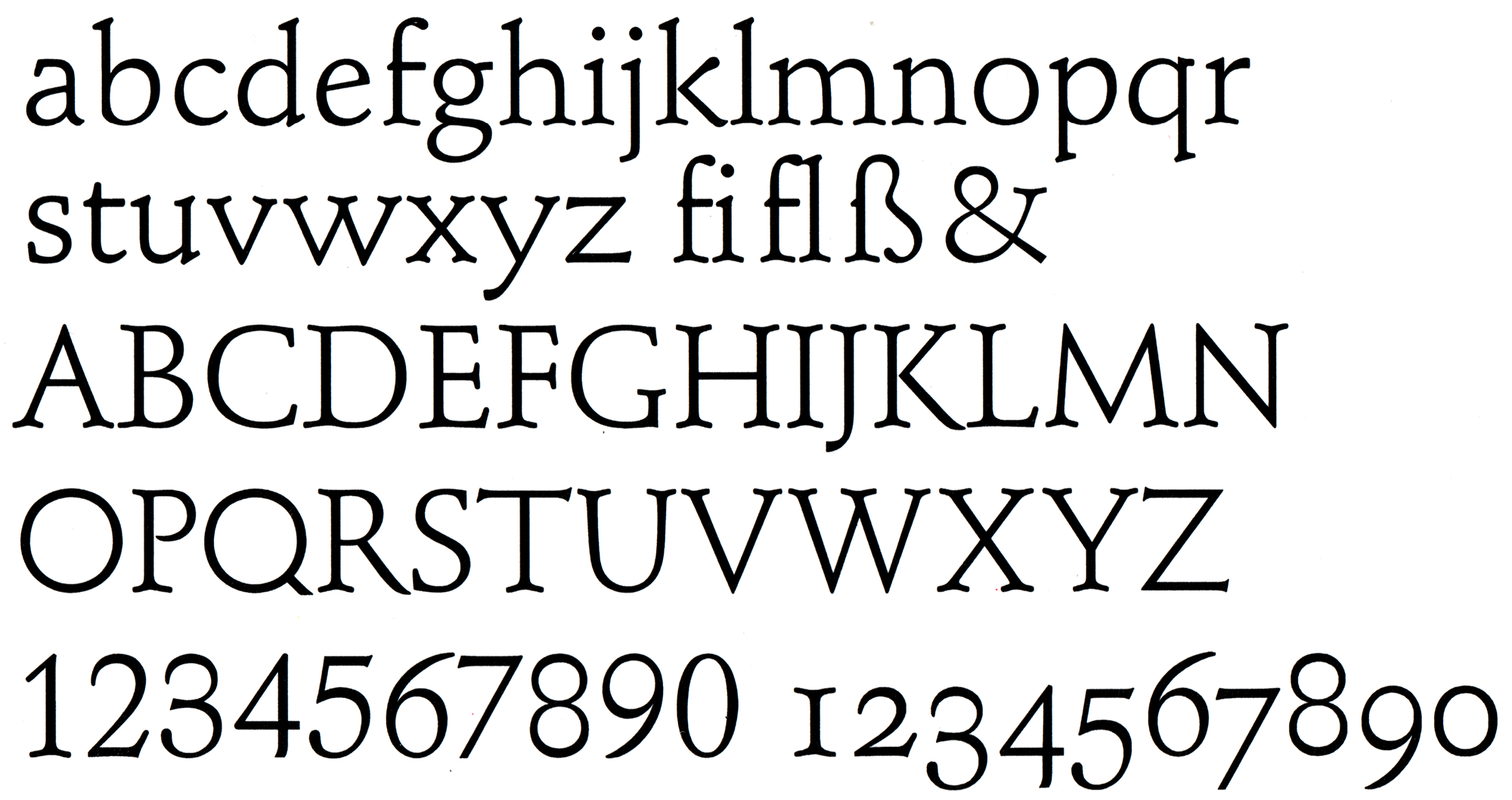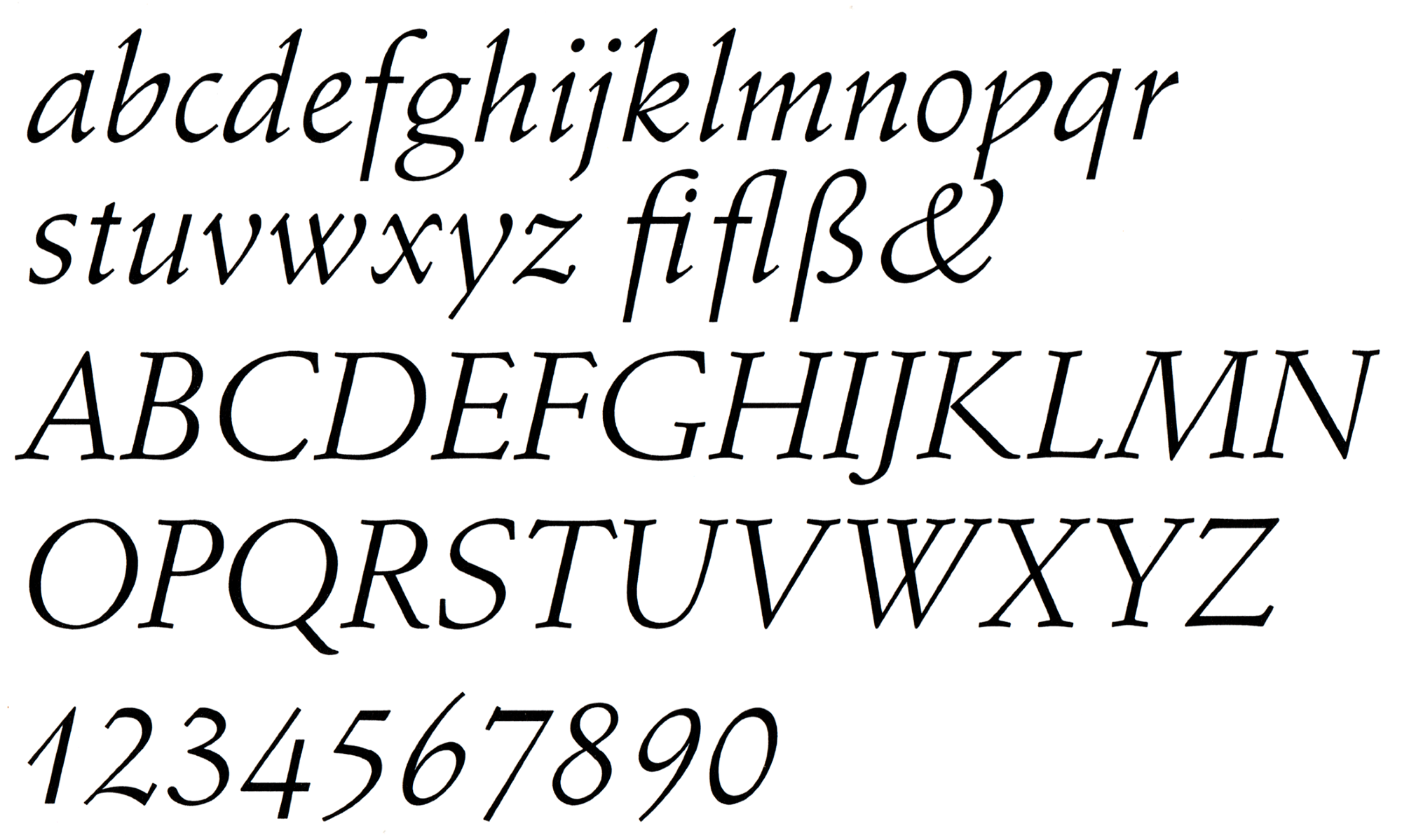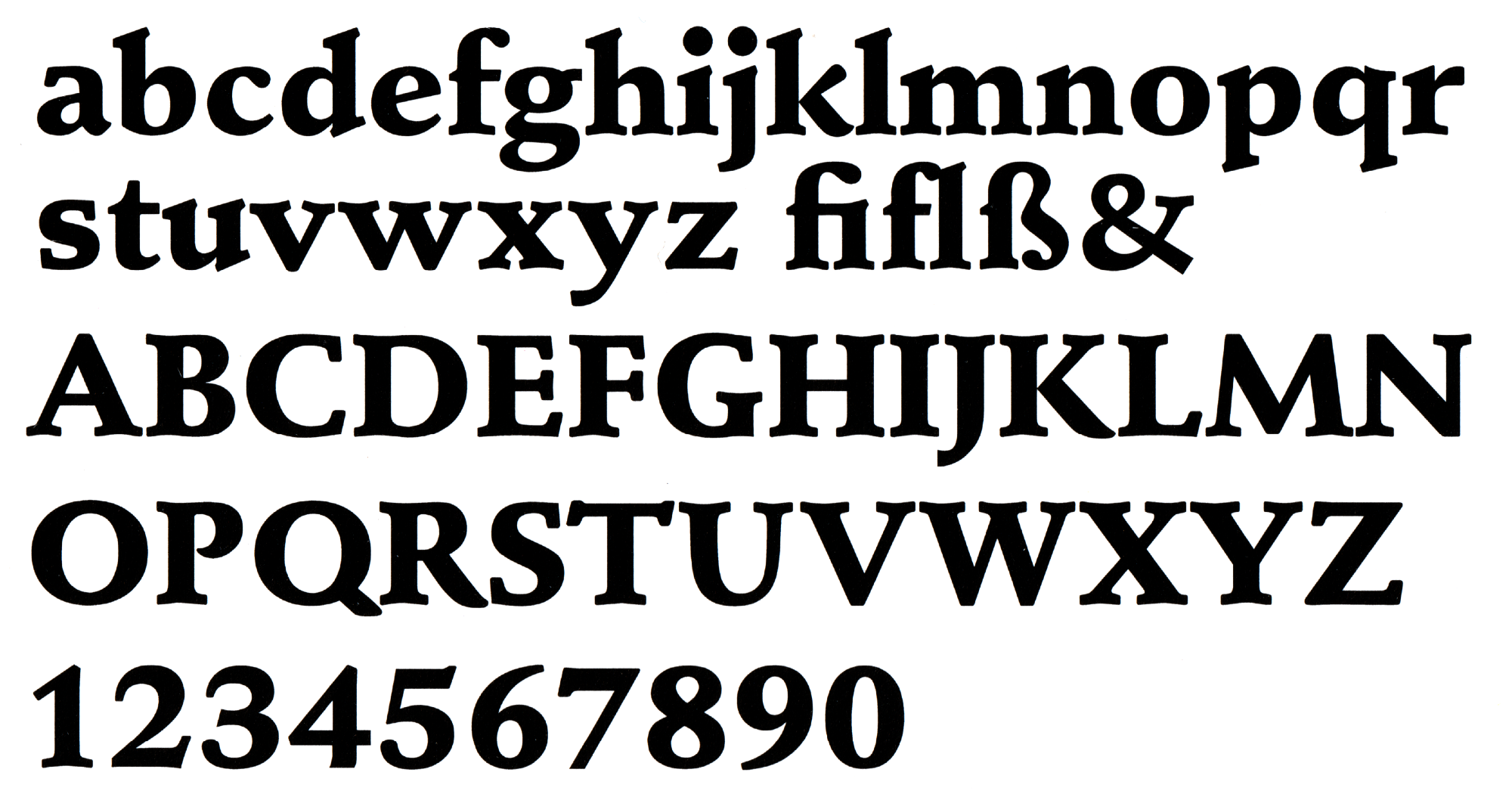
Font-Wiki: Stempel Schneidler
Die Schneidler-Mediäval erschien ursprünglich in den 1930er-Jahren in nur einem Schnitt. Anfang der 1980er-Jahre wurde der Entwurf bei der D. Stempel AG umfangreich ausgebaut und nun unter dem Namen Stempel Schneidler vermarktet.
Digitalisierungen mit bis zu fünf Strichstärken inkl. Kursiven sind zum Beispiel von Bitstream und URW erhältlich. Letztere hat einen größeren Zeichenvorrat.